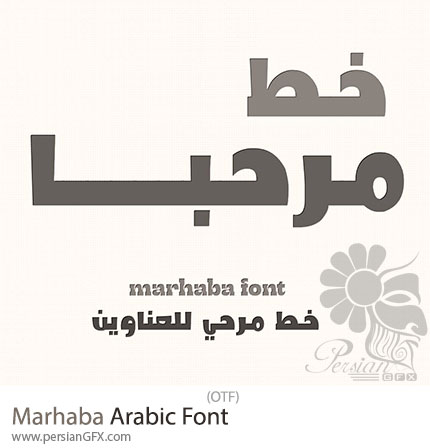
در این بخش شاهد فونت عربی مرحبا می باشید که با فرمت OTF بر روی سایت برای دانلود قرار گرفته است. Marhaba Arabic Font یک فونت مدرن و شیک عربی است که برای طراحیهای دیجیتال و چاپی فوقالعاده مناسب میباشد. این فونت ترکیبی از زیبایی سنتی خوشنویسی عربی و سادگی مدرن را ارائه میدهد که آن را به گزینهای عالی برای طراحیهای متنوع تبدیل کرده است.